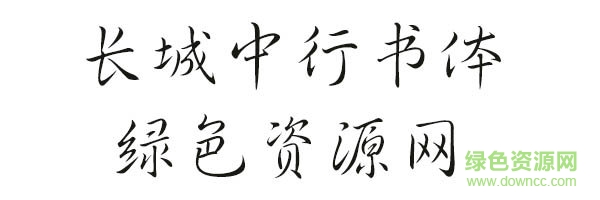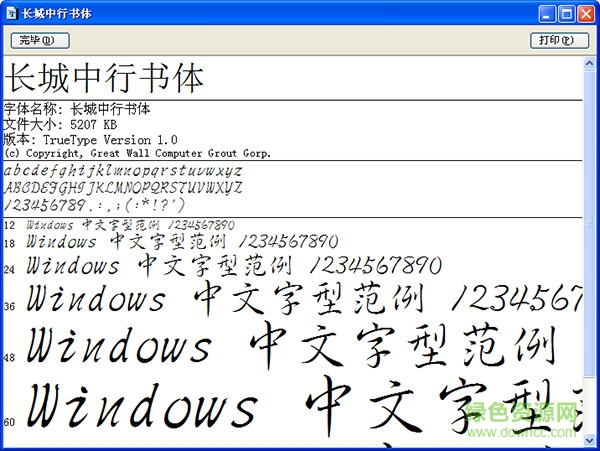
長城中行書體是一款為電腦用戶準(zhǔn)備的字體軟件,它的字型有點(diǎn)像秀麗筆寫出的感覺,字體端正,非常清秀。喜歡的朋友趕緊來綠色資源網(wǎng)下載吧!
長城中行書體是一款有著超強(qiáng)設(shè)計(jì)感的字體,有點(diǎn)像毛筆字,只是比毛筆字要細(xì)一些而已!